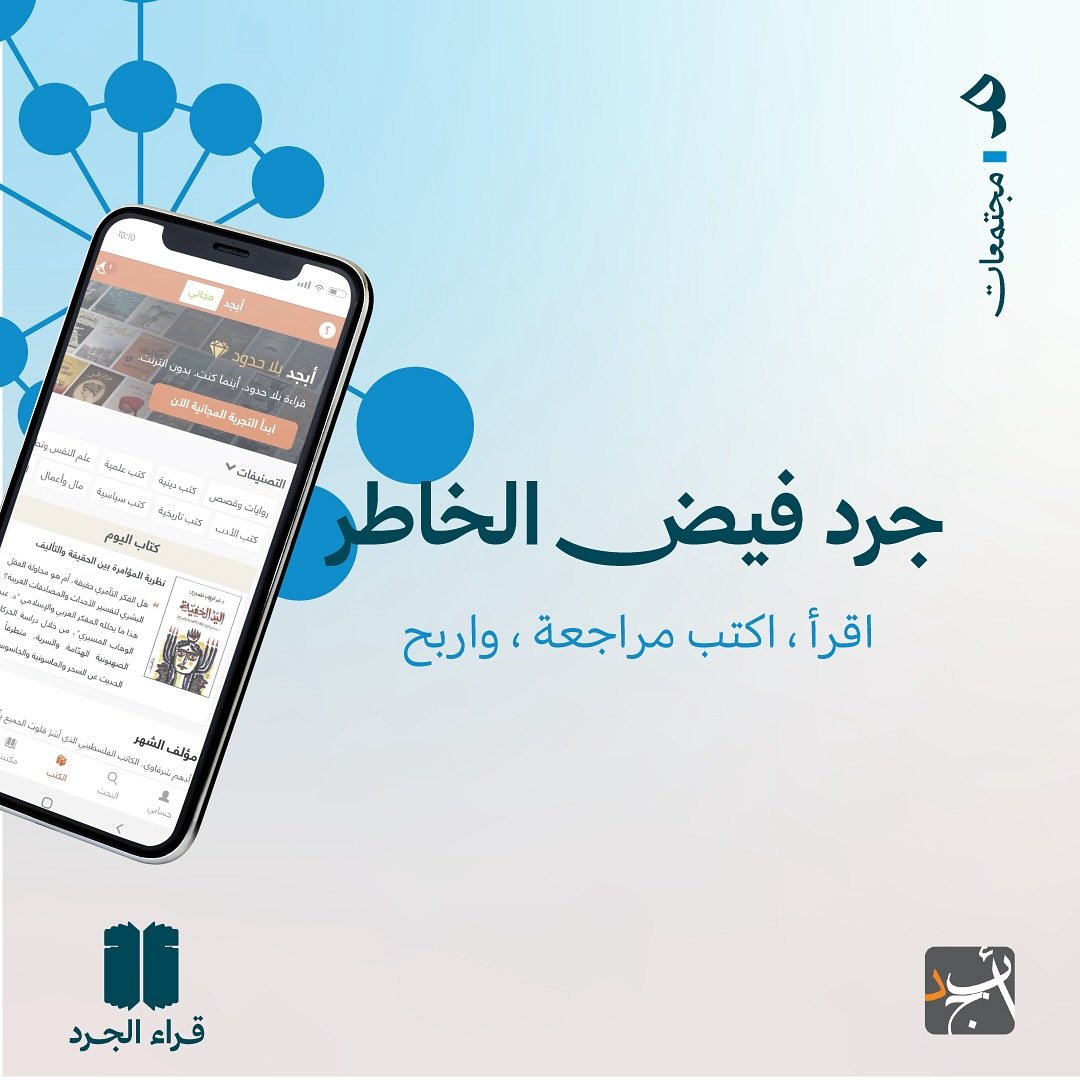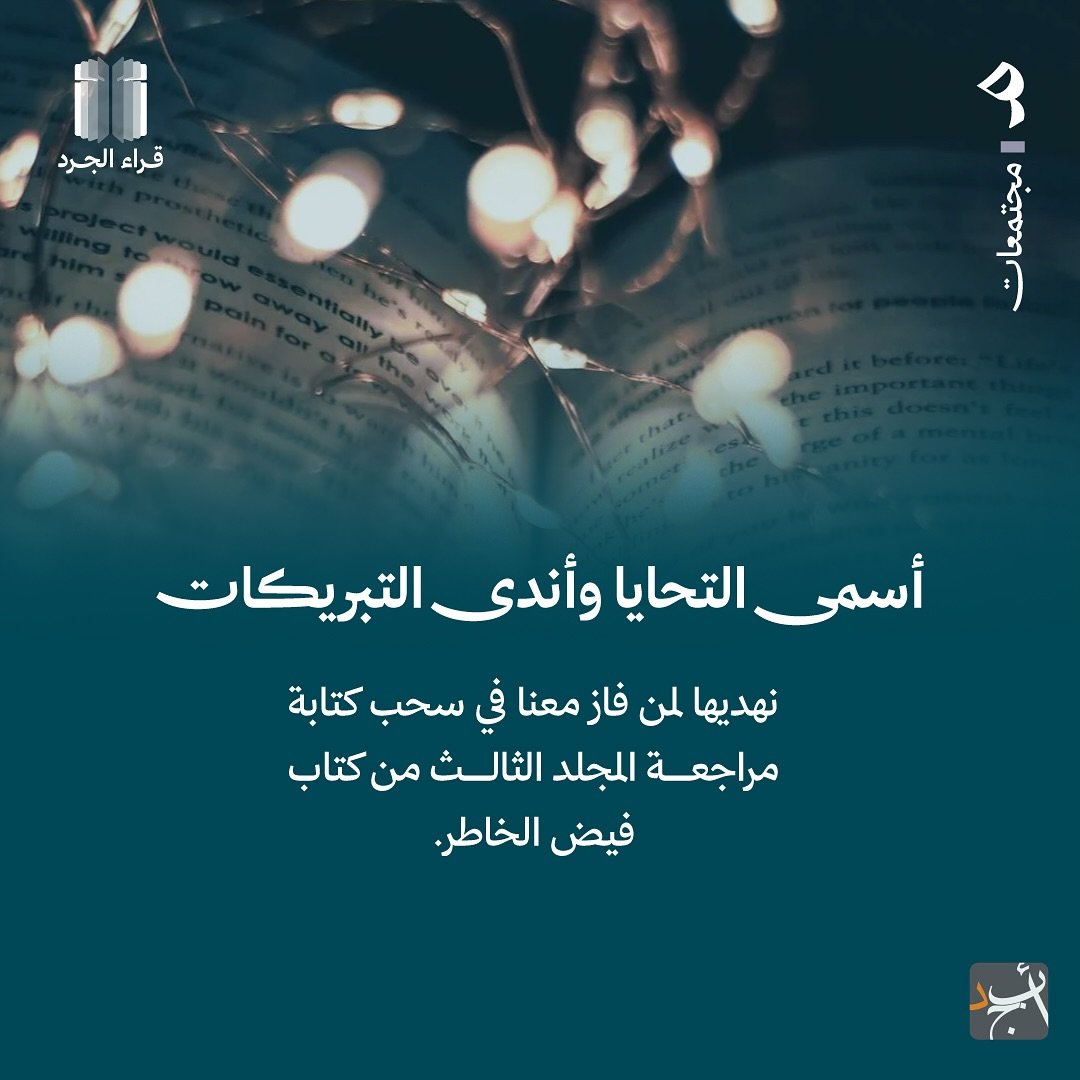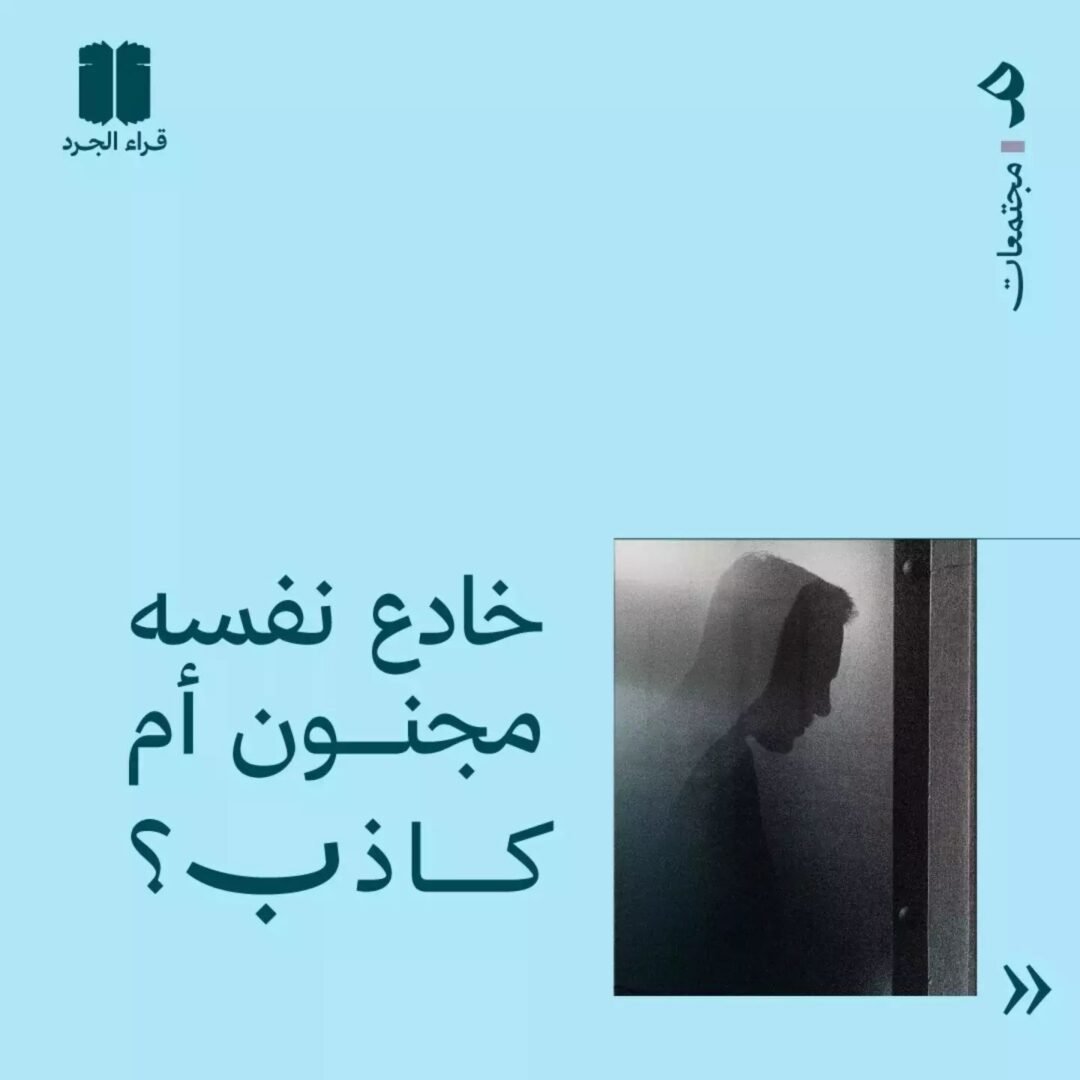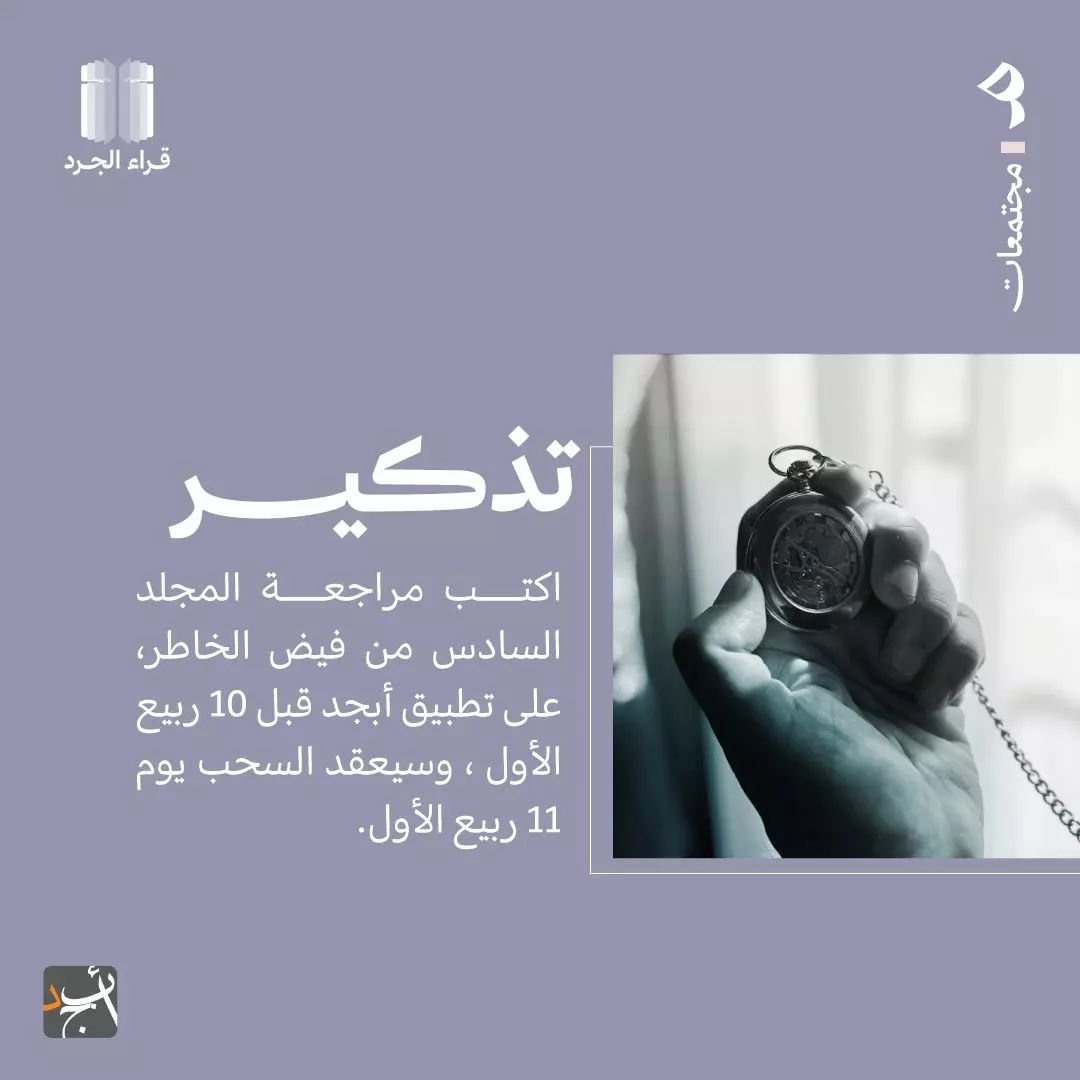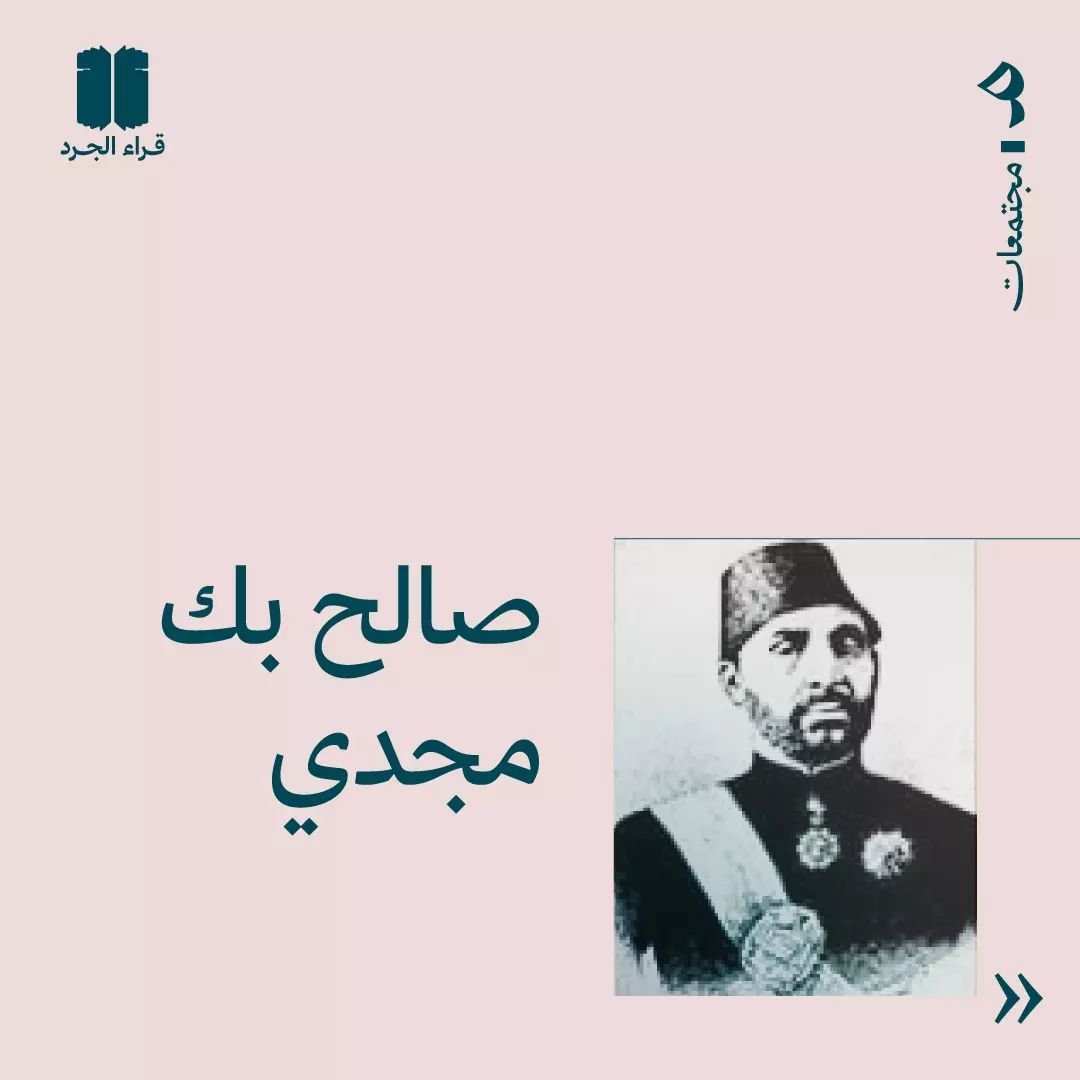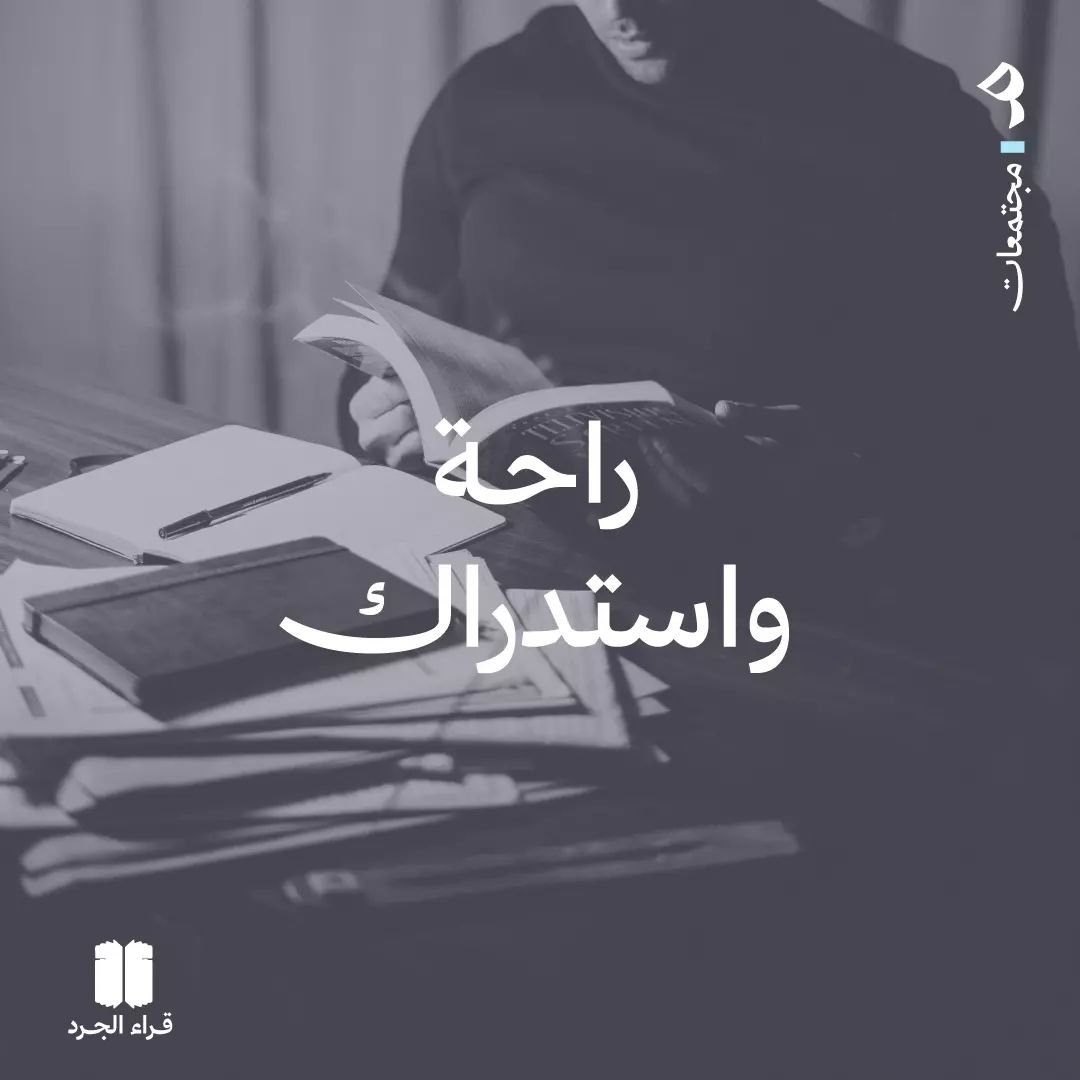
استخدام خط دهب – قُرّاء الجَرد
دهب هو خط عربي حديث صممه احمد ظاظا . التصميم مستوحي من اسلوب النسخ . و النتيجة هي مزيج يجمع بين النسب الحديثة و النصوص العربية الكلاسيكية . انها مناسبة للعلامات التجارية و التحرير التعبيئة و الاعلان . دهب عربي يتميز بخمسة اوزان من العادي الي الاسود .